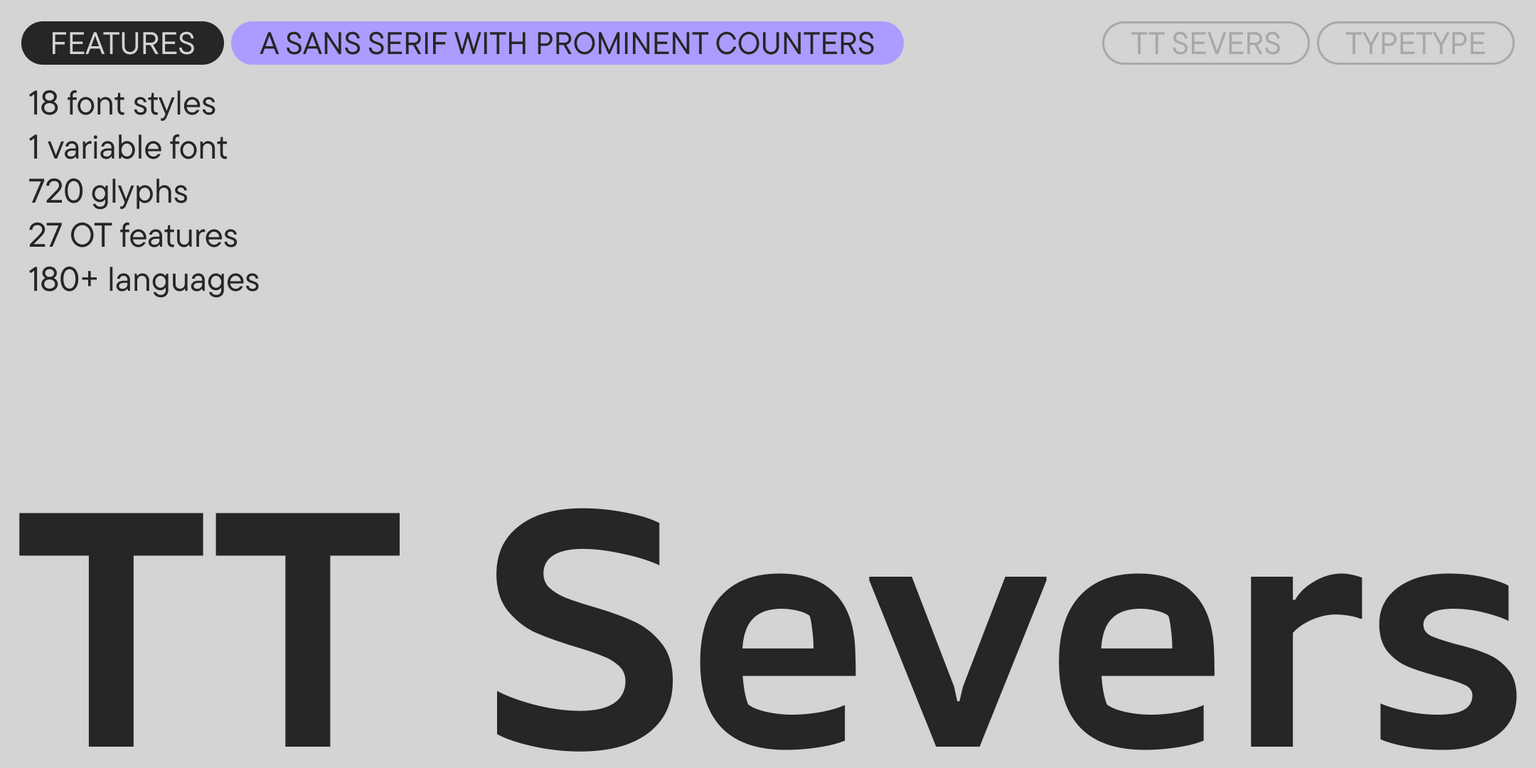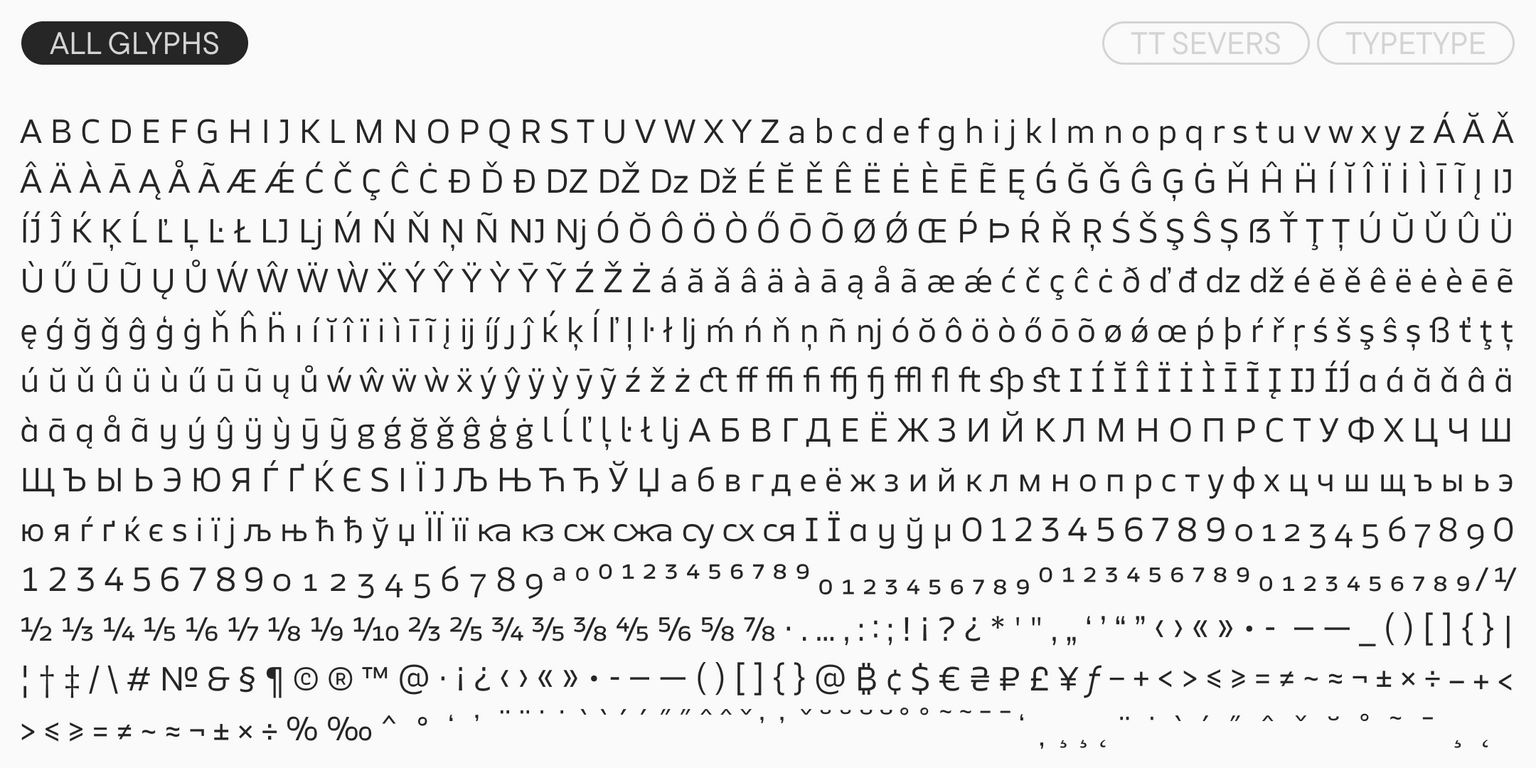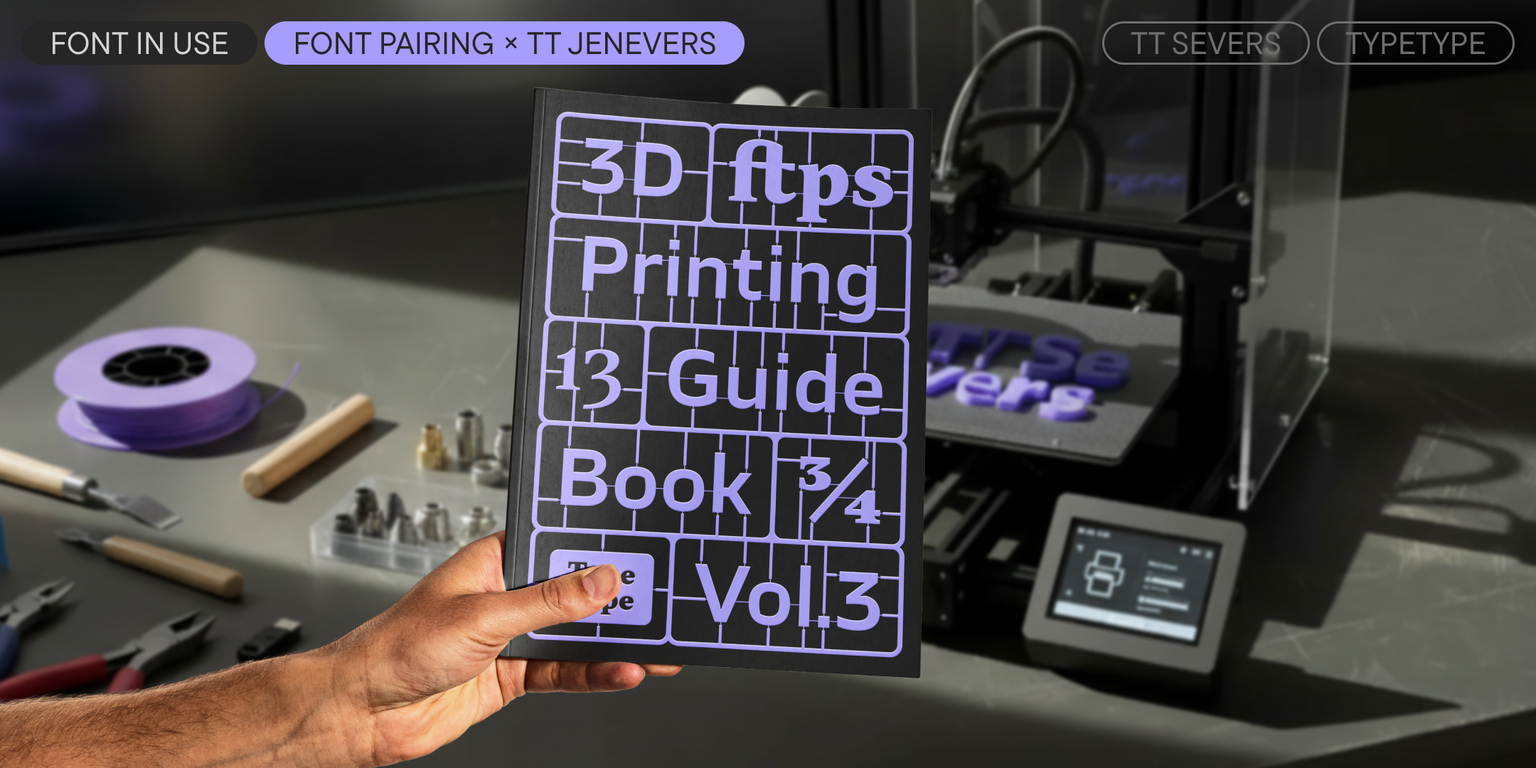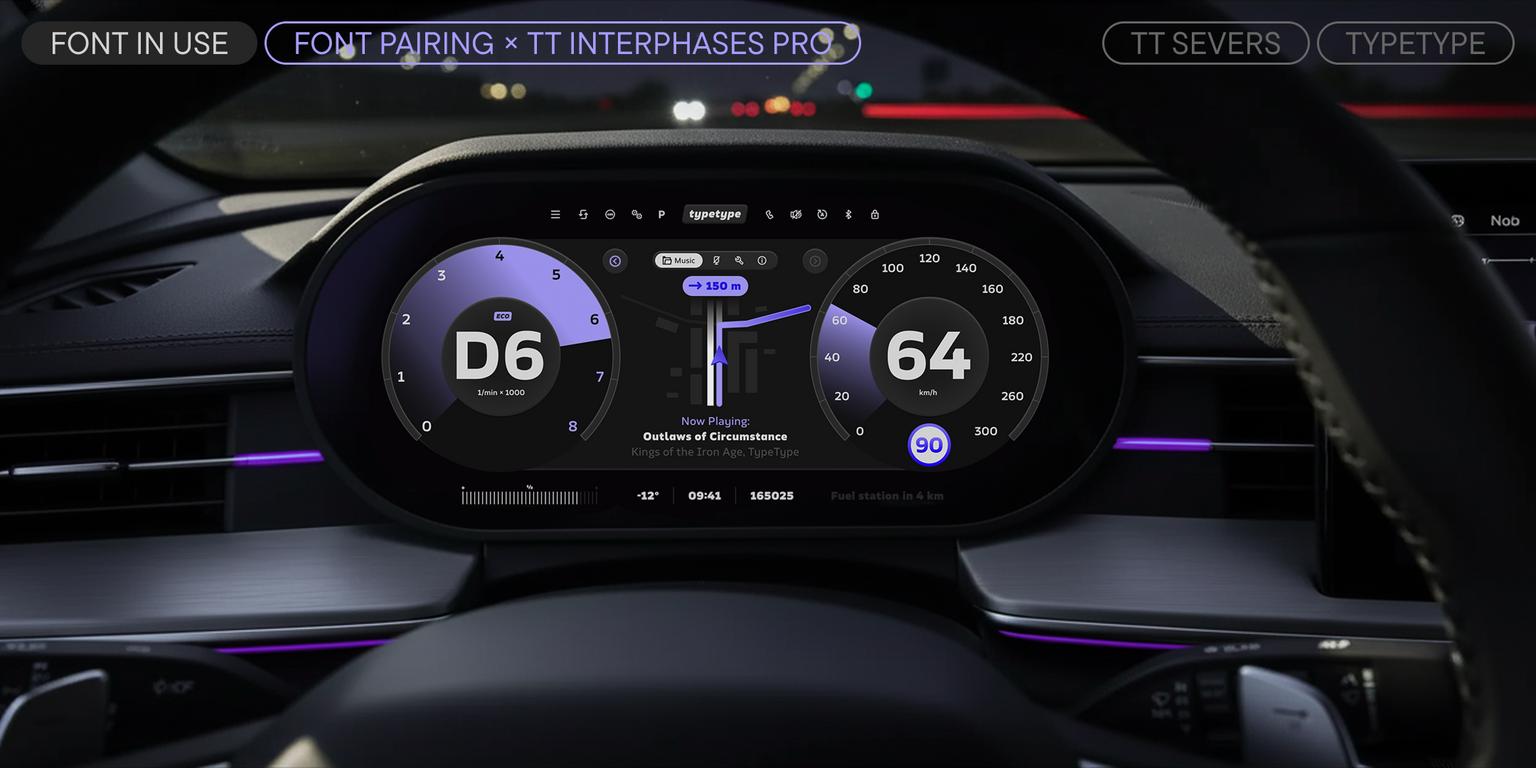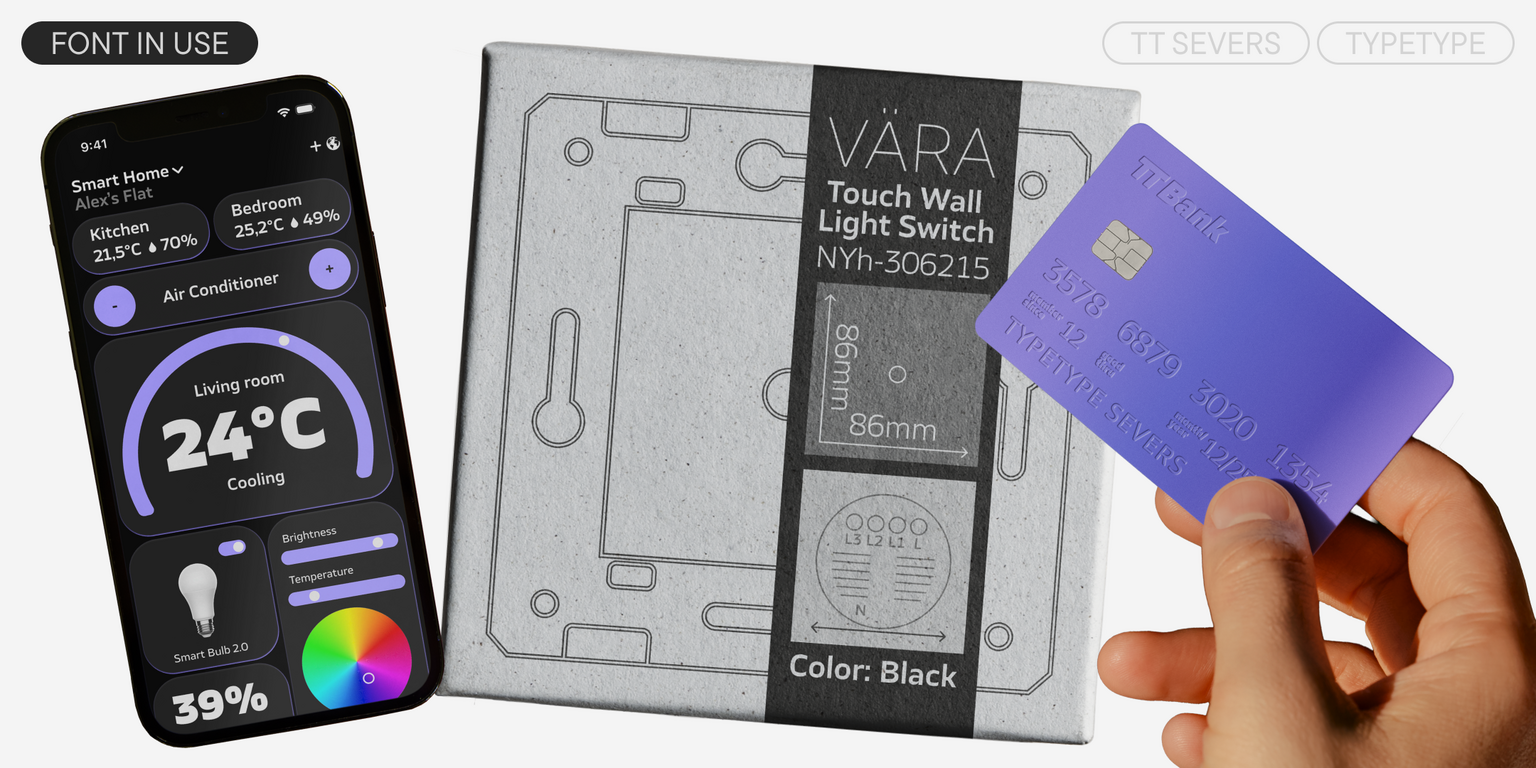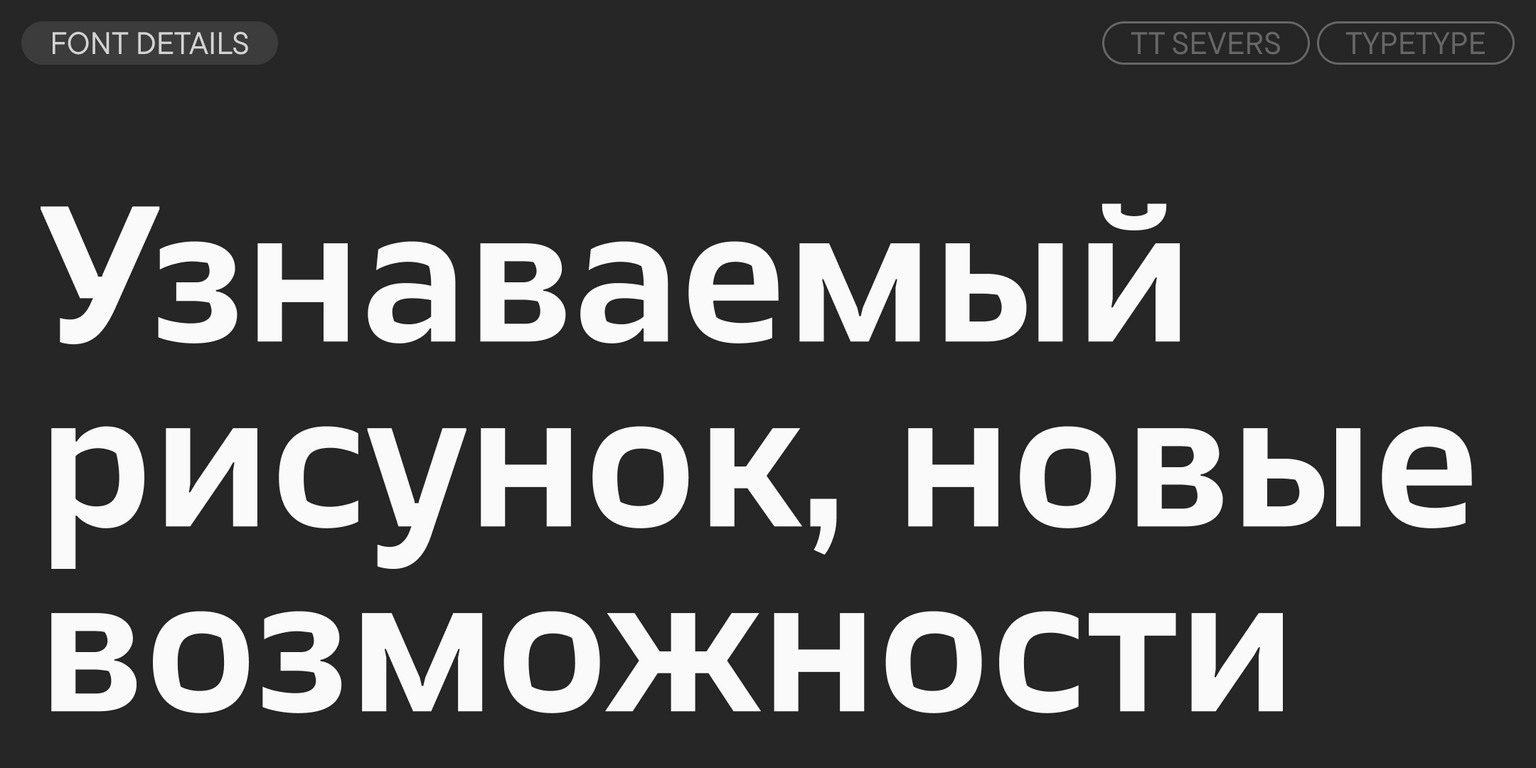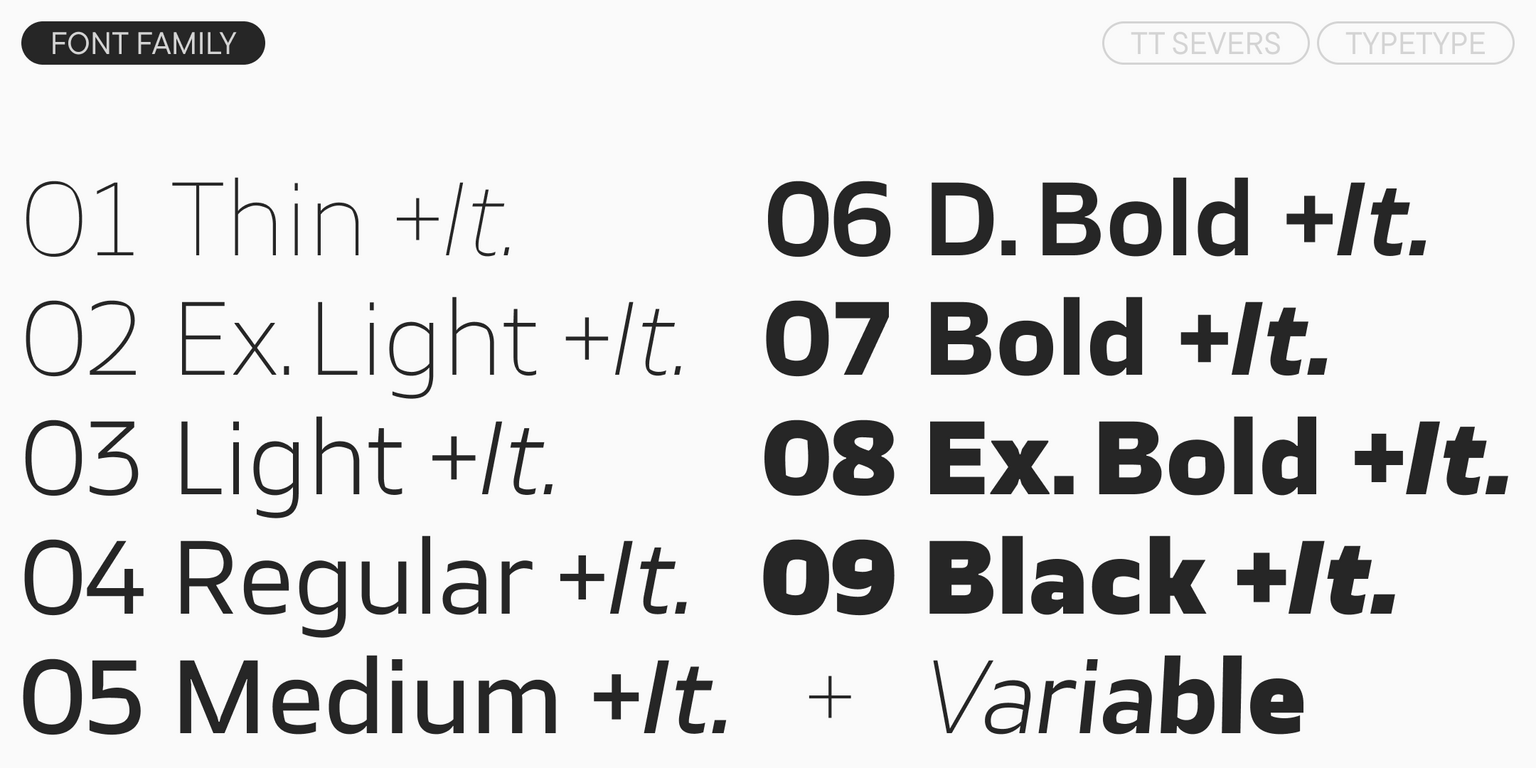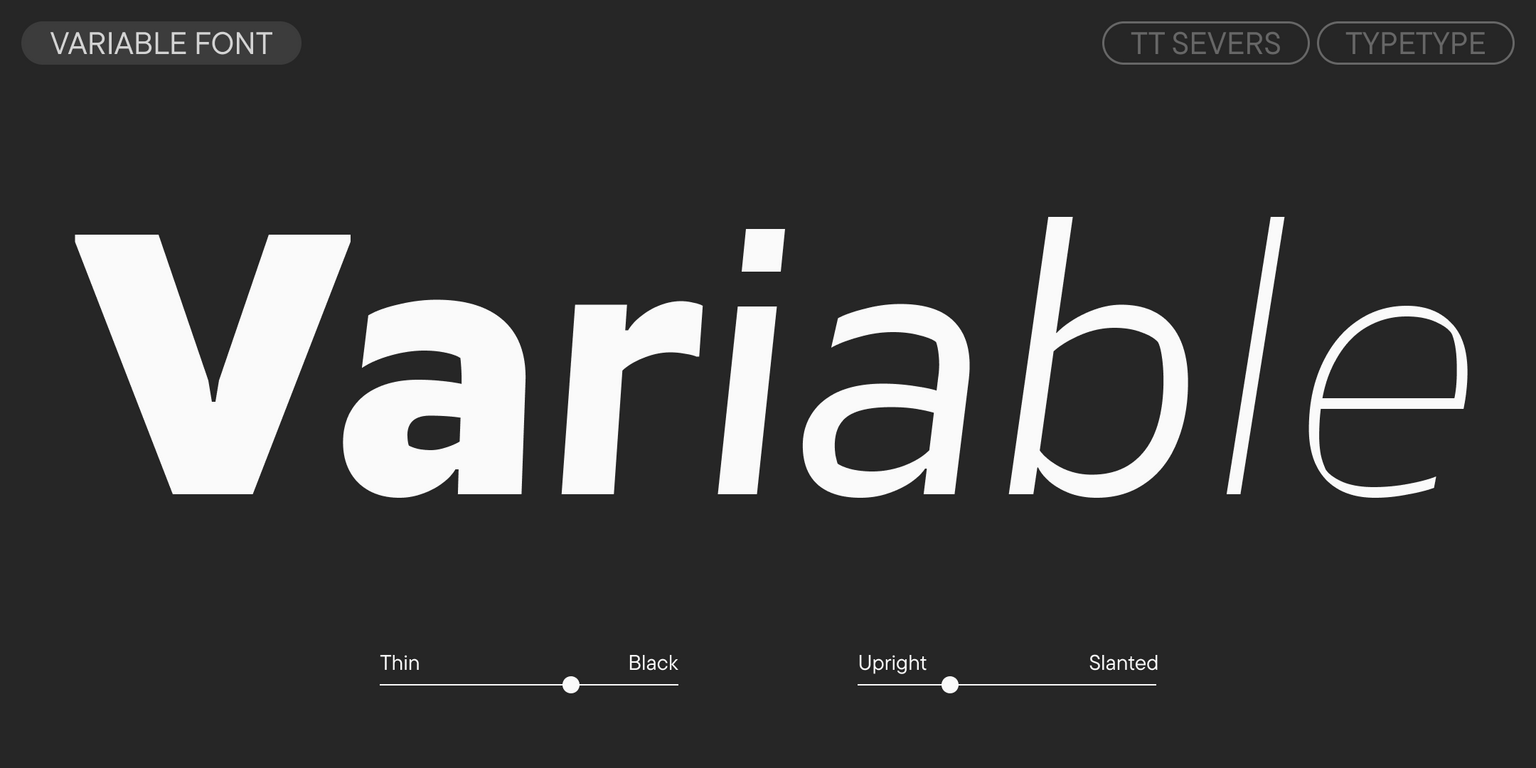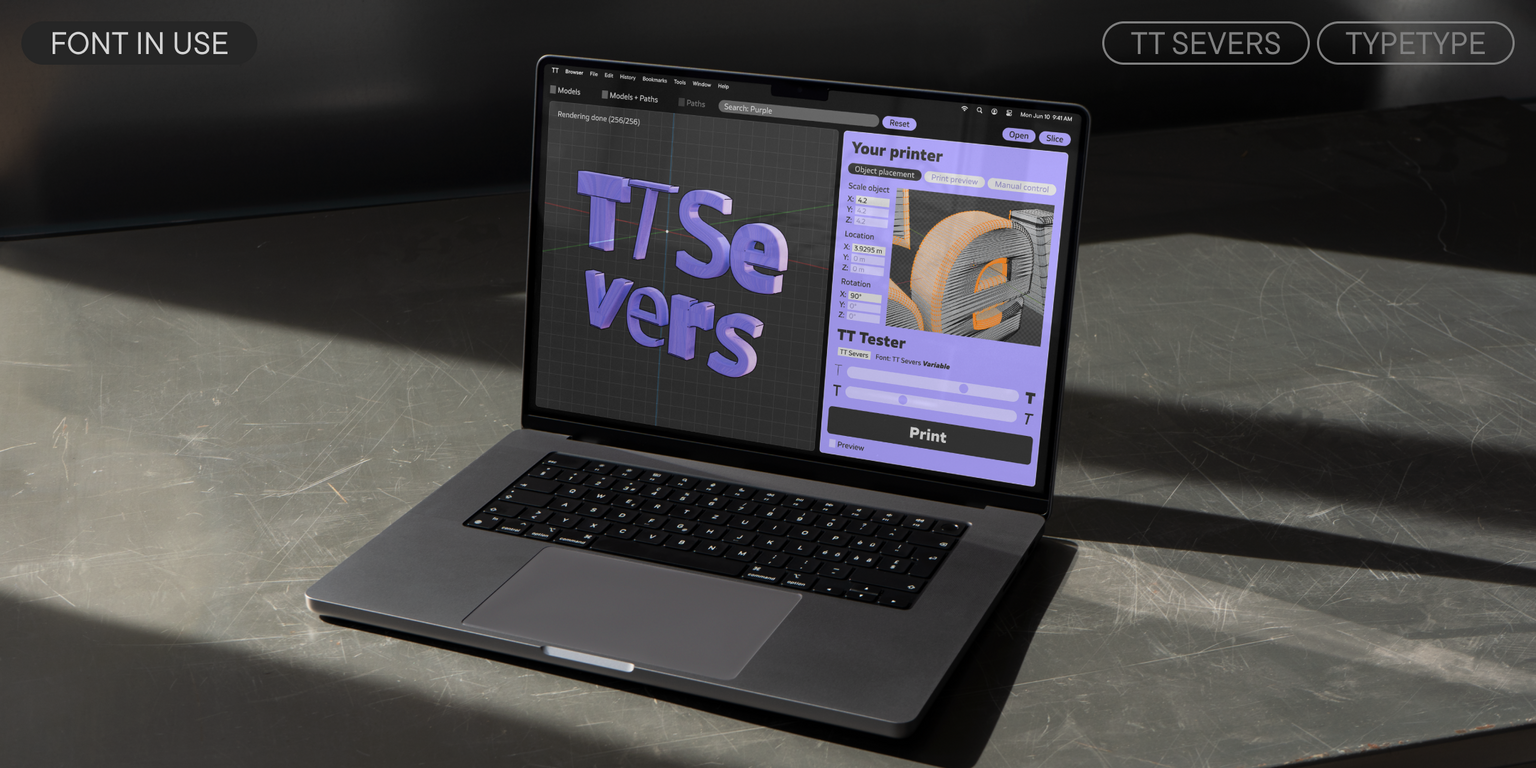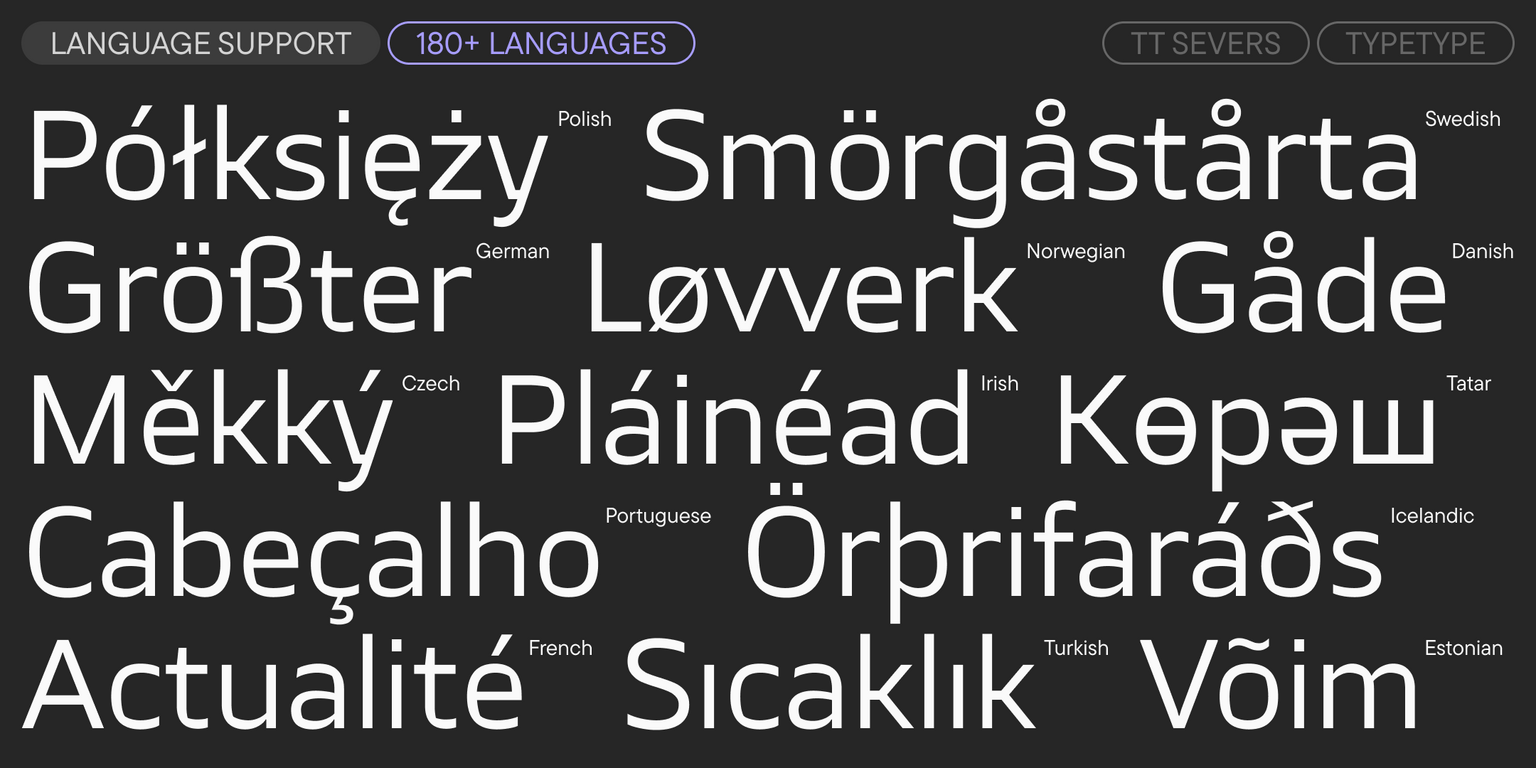
TT Severs
TT Severs — ТТ Северс
Произносится «ТТ Северс». «Severs» — производное слово от sever, в переводе с английского «разрывать», отсылка с рублёным элементам скругления овалов. Буквы «TT» являются аббревиатурой названия компании
TT Severs — геометрический гротеск с необычной формой внутренних овалов, которая отсылает к стилю традиционной арабской письменности. В крупном размере он работает как акцидентный шрифт, а в мелком — как текстовый.
TT Severs
Гротеск с ярко выраженными элементами внутренних скруглений
TT Severs
TT Severs — два характера в одной гарнитуре. В крупных размерах TT Severs работает как выразительный акцидентный шрифт, демонстрируя яркий характер и индивидуальность. В мелком кегле и при наборе больших текстовых массивов скругления становятся менее заметными, и гарнитура уверенно выполняет роль текстового шрифта. Это стало возможным благодаря умеренному контрасту между штрихами и тщательно выверенному балансу чёрного и белого в знаках. Гарнитура отличается решительным и твёрдым характером, что делает её идеальным выбором для сферы IT, компьютерных игр и спортивной индустрии.
В 2025 году мы добавили вариативный шрифт и 8 новых альтернативных сетов
О гарнитуре TT Severs
Встречайте обновленный TT Severs версии 2.000! Добавили новые функции, знаки и языки, а также вариативное начертание.
TT Severs — это гуманистический гротеск с открытым характером и яркими элементами. Отличительная особенность этого шрифта — необычная форма внутренних овалов, примыкания которых отсылают к каллиграфической основе.
TT Severs — гарнитура два в одном. В большом кегле шрифт раскрывается в деталях и прекрасно работает как акцидентный, добавляя логотипам и заголовкам характерности. При этом в маленьком кегле или в больших массивах текста особенности построения скруглений отходят на второй план, и шрифт отлично читается — в том числе благодаря низкому контрасту между вертикальными и горизонтальными штрихами, а также детально продуманной логике взаимодействия чёрного и белого в рисунке знаков.
В гарнитуре есть стандартные и дискретные лигатуры, в том числе экспериментальные лигатуры для кириллицы. Кроме того, TT Severs можно сделать более мягким с помощью стилистических альтернатив. В обновлённой версии вы найдёте ещё больше OpenType фич и стилистических сетов, а ещё — вариативный шрифт, меняющийся по осям жирности и наклона. Также мы добавили новые языки и служебные глифы. В частности, дорисовали минускульные математические знаки и дополнили латиницу. Усовершенствовали и техническую составляющую шрифта — полностью обновили кернинг и хинтинг.
TT Severs — универсальный шрифт, который в разных начертаниях можно использовать для разных задач. Он отлично впишется в дизайн, связанный с технологиями, компьютерными играми, спортом и другими сферами.
В TT Severs 2.000 входит:
• 19 начертаний: 9 прямых, 9 наклонных и 1 вариативный шрифт;
• 720 знаков в каждом начертании;
• 27 OpenType фич;
• Поддержка 180+ языков.
Что изменилось в шрифте:
• Количество OpenType фич увеличилось с 16 до 27;
• Количество начертаний увеличилось с 18 до 19;
• Появились новые стилистические сеты;
• Количество знаков увеличилось с 557 до 720. В частности, мы дорисовали минускульные математические знаки и дополнили латиницу;
• Количество языков увеличилось со 160+ до 180+;
• Полностью обновились кернинг и хинтинг.
ss04 | Alternative g
liga | Standard Ligatures
dlig | Discretionary Ligatures
onum | Oldstyle Figures
case | Case Sensitive Forms
frac | Fractions